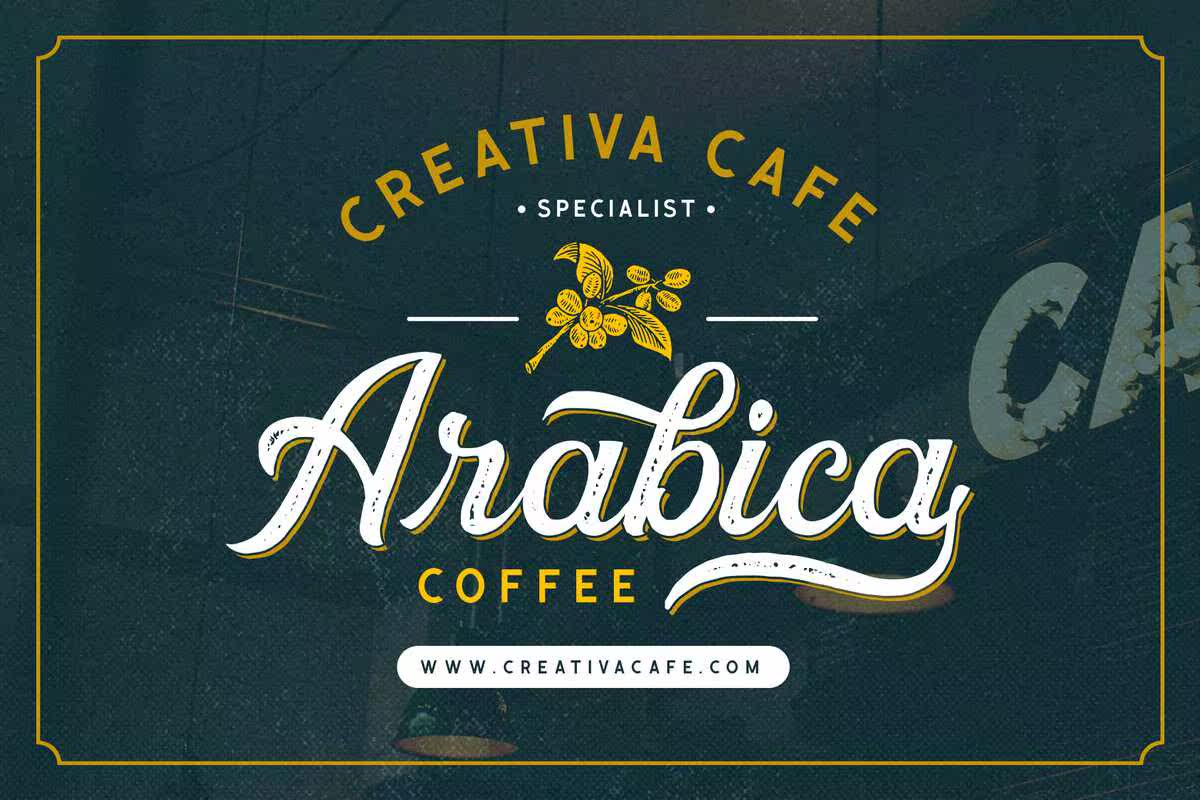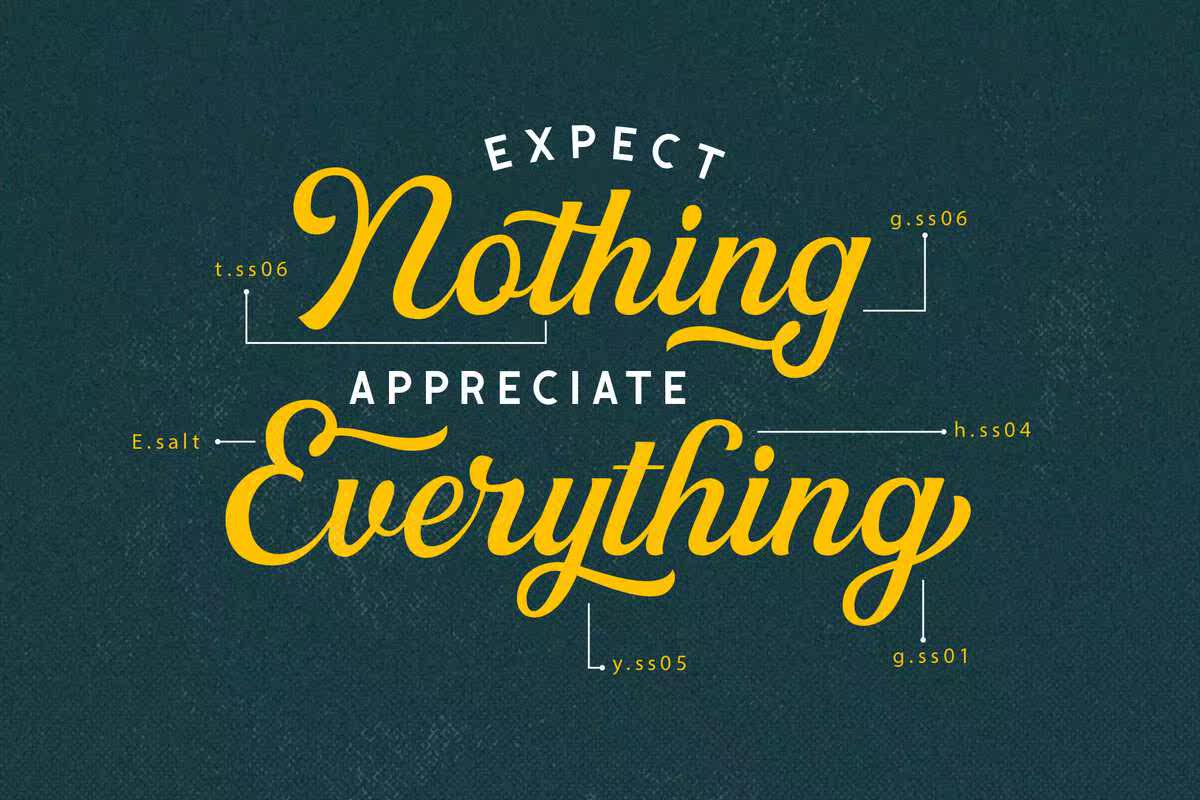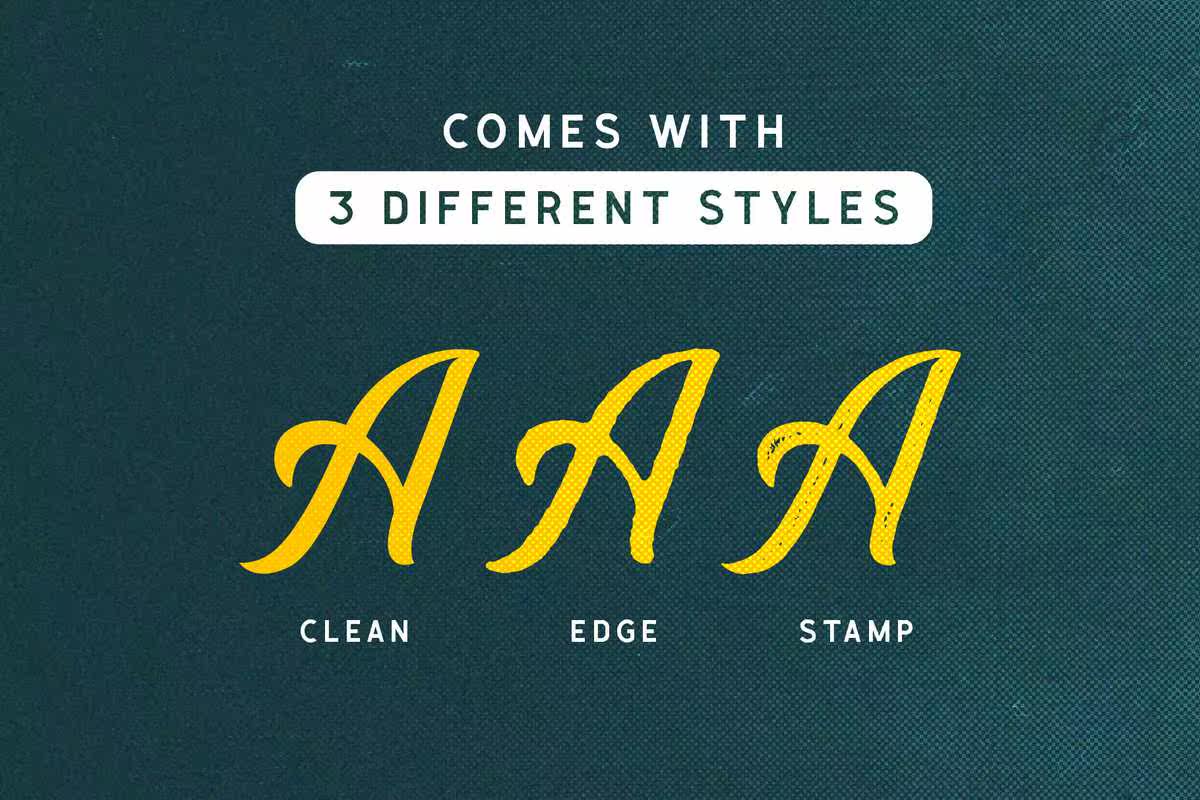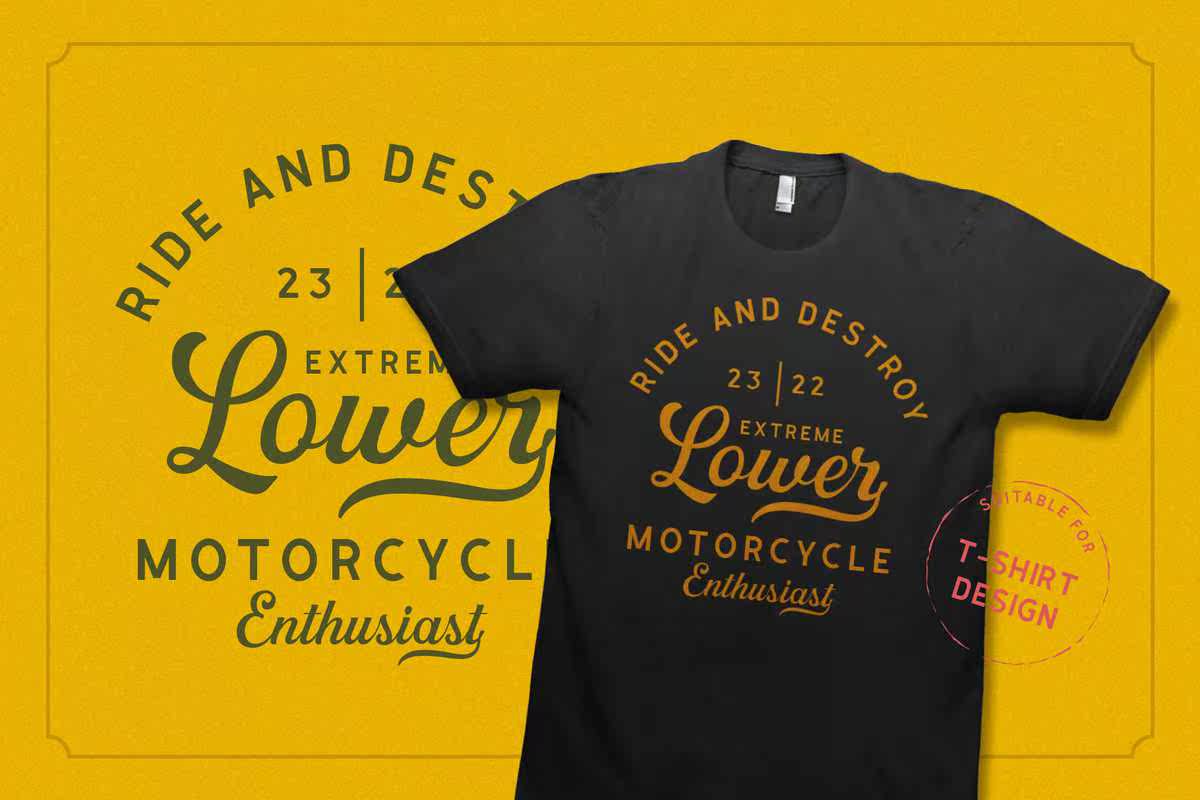
非常多的手写体和sans字体,非常完美。对于需要字体的用户来说,经典感觉非常完美,特别是标识、服装、邀请、品牌、包装、广告等。字体包括大写、小写、标点符号、符号和数字、文体设置、替换、连字、,ETCALS支持多语言和可读UAEncoded。非常丰富的手写体和sans字体。经典感觉非常适合需要字体的用户,特别是徽标、服装、邀请、品牌、包装、广告。该字体包括大写、小写、标点符号、符号和数字、文体设置、替换、连字、,ETCALSO支持多语言和alreadypuaencoded。